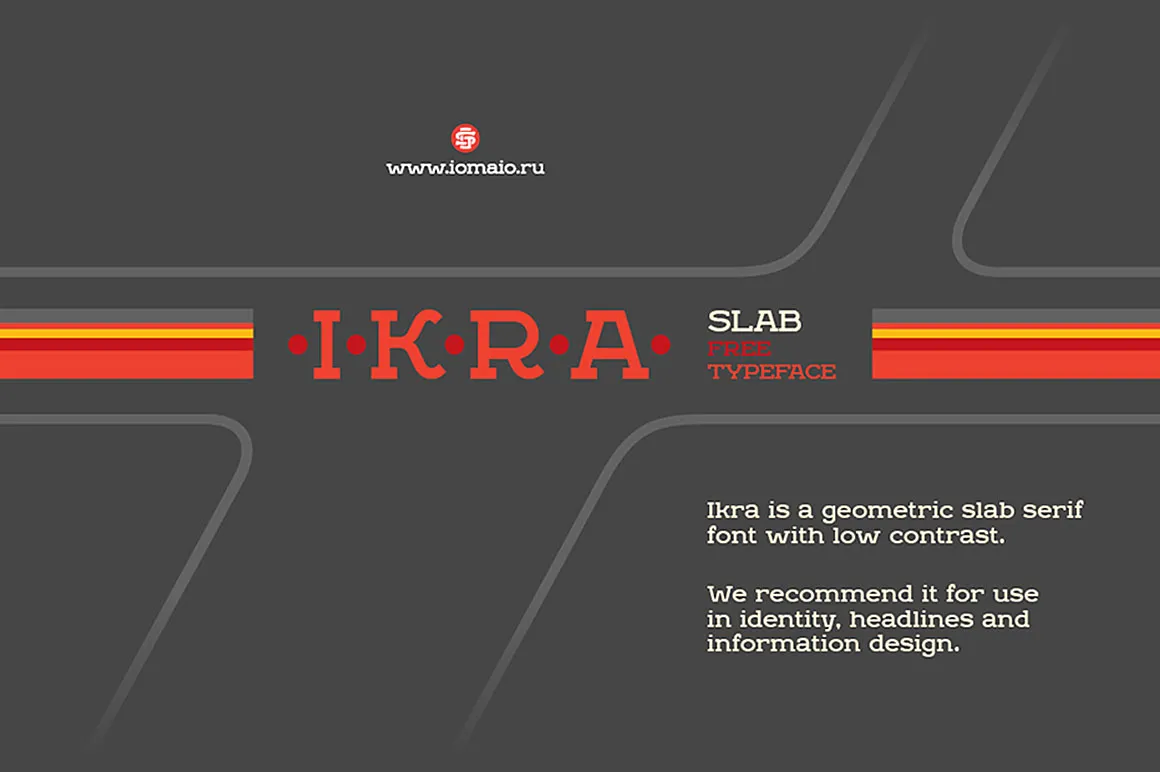
A Ikra Slab Font é uma customização criada pelo designer Sergey Godovalov, disponível para download e desfrutar. Embora não sejam características originais do texto fornecido, a fonte caracteriza-se por sua estrutura robusta e versátil, perfeitamente adequada para aplicativos como design gráfico e branding. Os traços sólidos e o estilo robusto da Ikra Slab trazem uma dose de modernidade aos textos em idiomas não-latinos, tornando-a uma opção inovadora para designers que buscam um toque único em seus projetos. A fonte foi criada especialmente com a variedade de escrita e facilidade de uso em mente, garantindo uma experiência de leitura harmônica. Com sua proposta atemporal, a Ikra Slab é uma escolha inteligente para quem procura expressar identidades únicas no design gráfico.